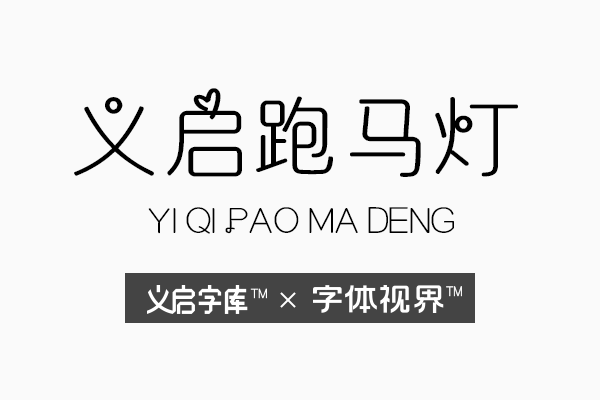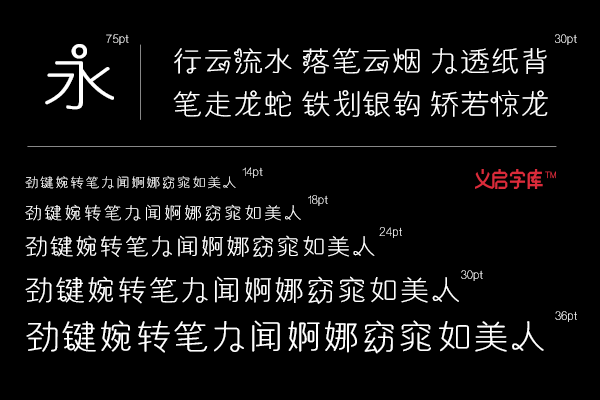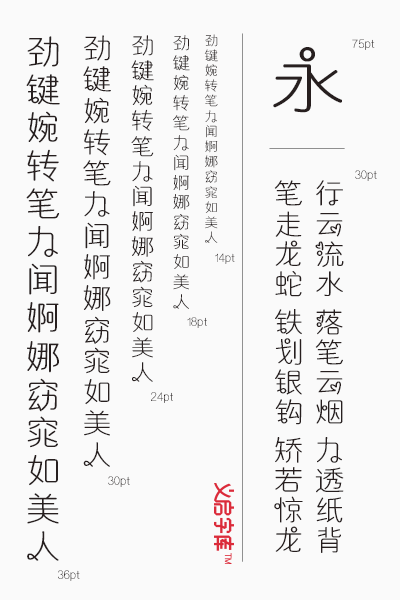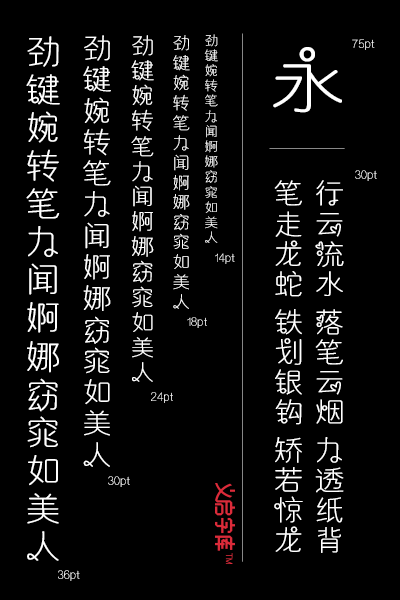
对于很多的人来说,都会有一种经常使用一种字体,就会让自己的视觉会产生一定的疲倦,所以经常更换自己的手机字体,让自己的视觉每天都有不一样的视觉体验吧。义启字库这一次推出的义启跑马灯字体,听起来就是非常的酷的,想要酷一点的你使用义启跑马灯字体一定会是一个不错的选择。
义启跑马灯字体,它的设计是非常的酷的,简单的笔画却有着跑马灯一样的既视感。那么问题来了,义启字库推出的这一款字体的特点在哪里呢?它是怎么样吸引到人们使用它的呢?
其实吧,义启跑马灯字体,它的设计是非常的简单的,我相信,任何一个人都是见过跑马灯的吧,这就是这种字体的设计来源。
义启字库对于这种字体的设计可谓也是花费了不少的精力呢,所以在设计的时候将自己也融入了一些可爱的风格。这种字体看起来是非常的讨喜的。所以很多人都想要下载这个字体,然后使用它。
定期的更换自己手机字体,就会让自己的视觉有不一样的体验,别让自己的视觉感到审美疲劳啊,义启跑马灯字体,这种可爱有带有一点酷的字体,难道是真的没有吸引到你吗?